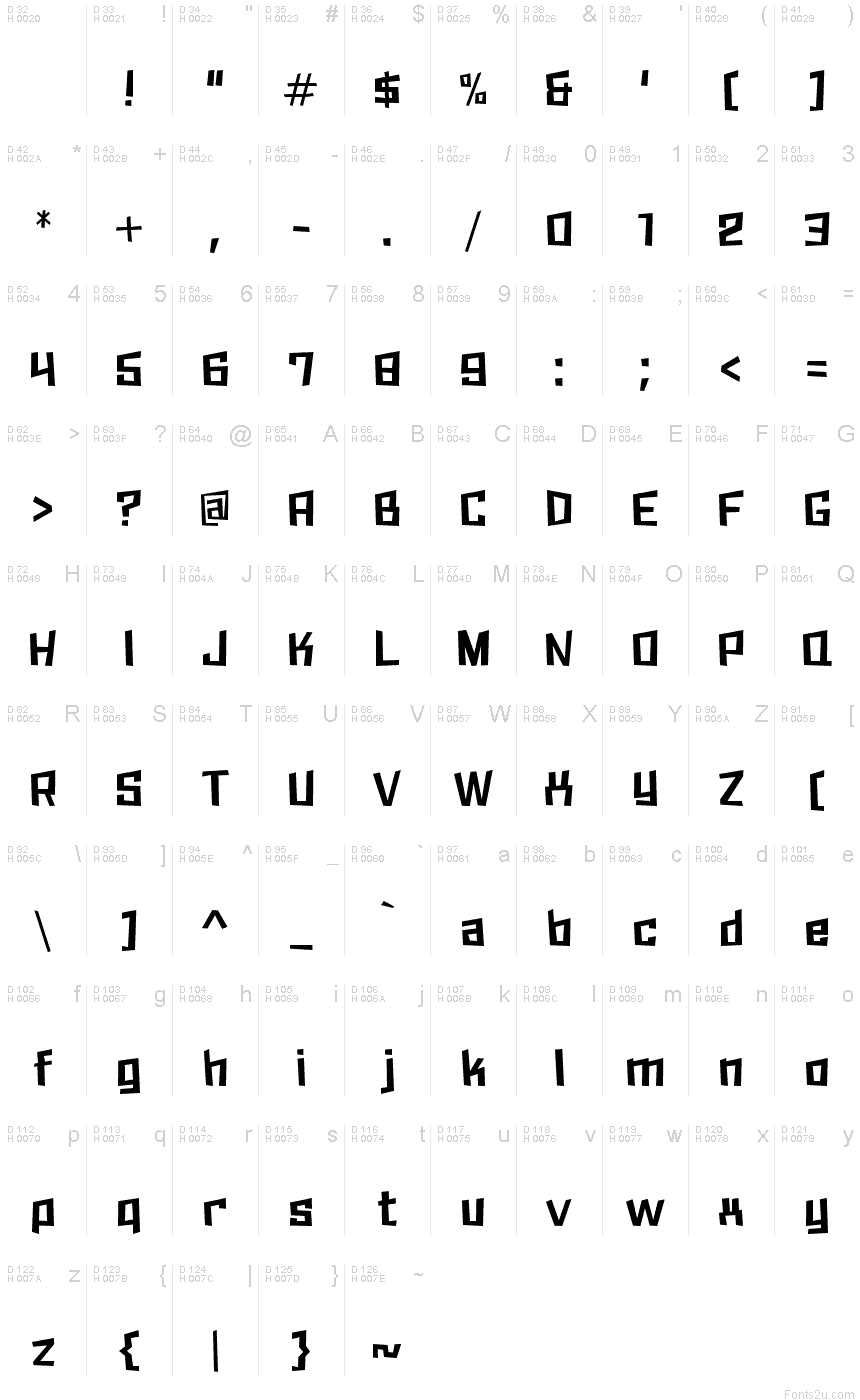
Updike od Tepid Monkey Fonts je bezplatné kreslené písmo s charakterem papírové koláže. Písmena sází na ostré hrany, nerovnoměrné úhly a masivní siluety, které působí trochu nespoutaně a ručně kresleným dojmem. Fontu to dodává hravou náladu indie komiksů z roku 2000, daleko od uhlazeného a vyleštěného vzhledu.
Uplatní se v nadpisech plakátů, na obálkách zinů, titulcích letáků, v herní grafice nebo na vizuálech kapel, kde hledáte tu správnou dávku nekonvenční, domácí energie. Jakožto bezplatný font se Updike hodí i pro krátké webové bannery nebo úvodní karty, zejména když potřebujete, aby pár slov mělo úderný, svérázný tvar, který je výrazný, aniž by působil příliš přátelsky nebo zakulaceně.